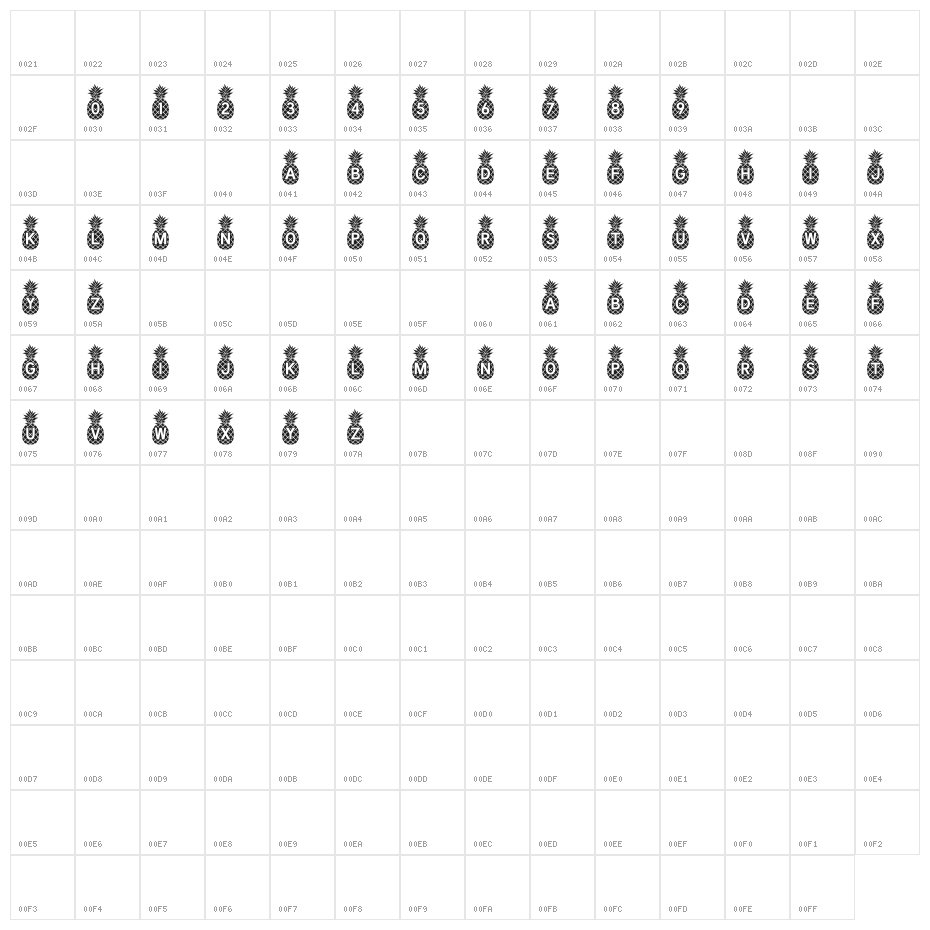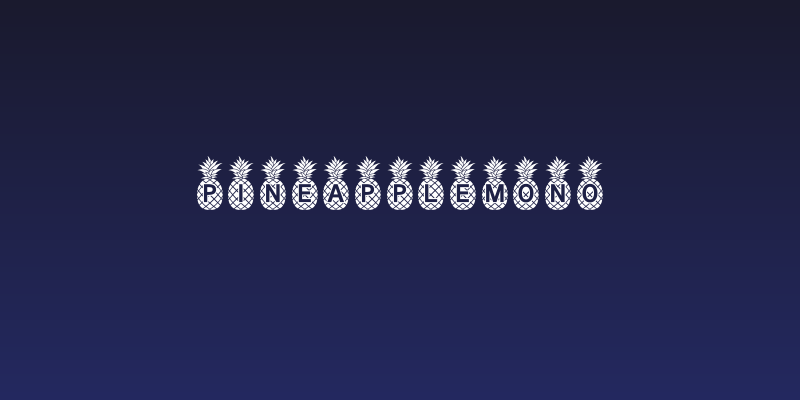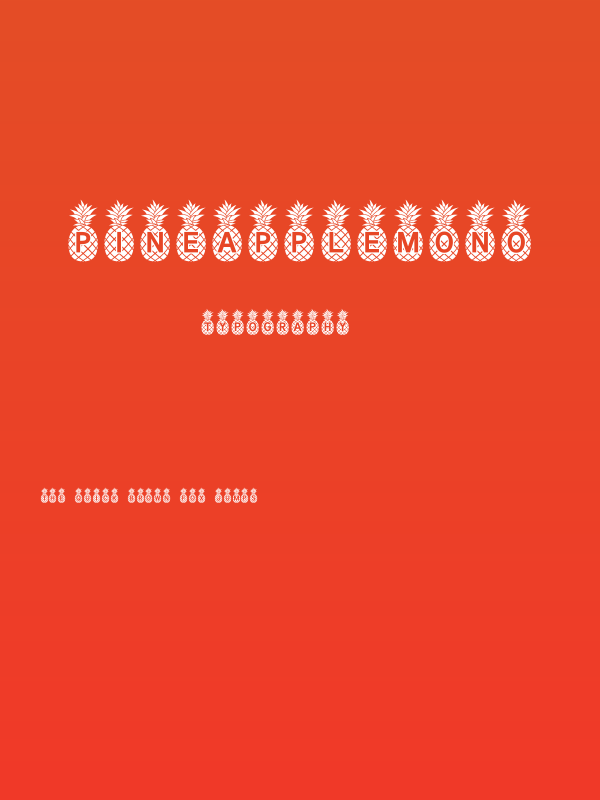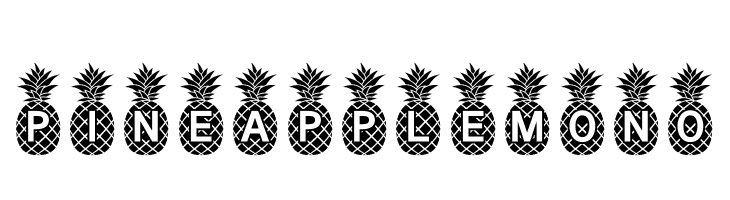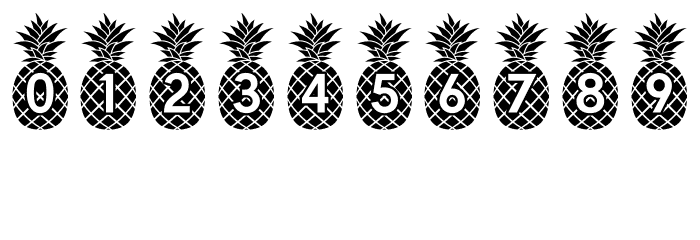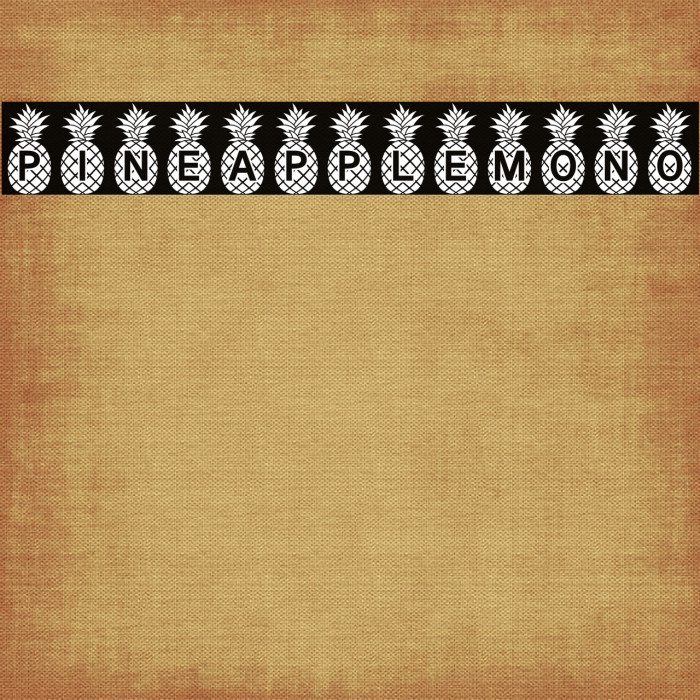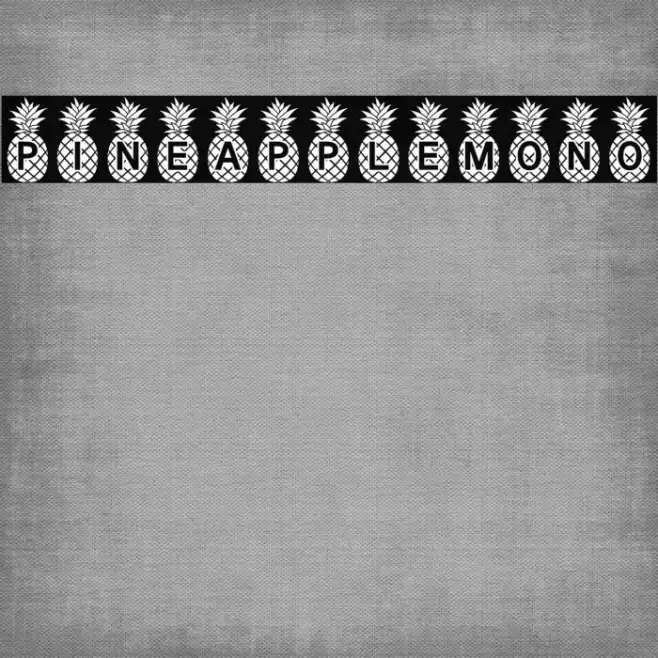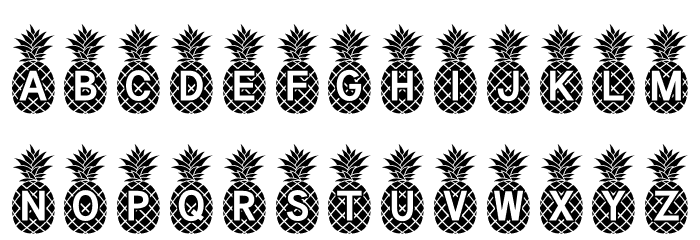
Pineapple_Mono Font
✎ Decorative
| Categorías | Decorative |
| Caso de uso | Logos, Invitations, Posters |
| Proyectos propuestos | Ideal for party invitations, tropical-themed events, branding for fruit-related products, or playful graphic design projects. |